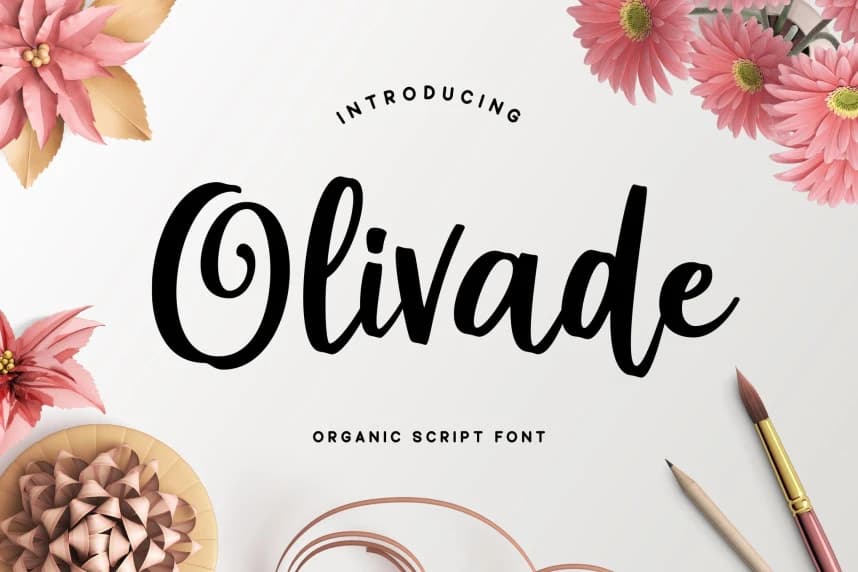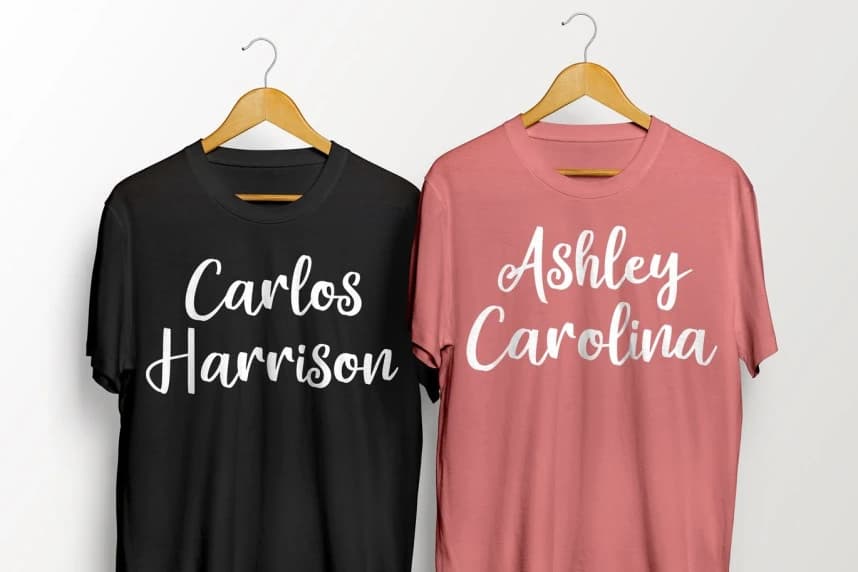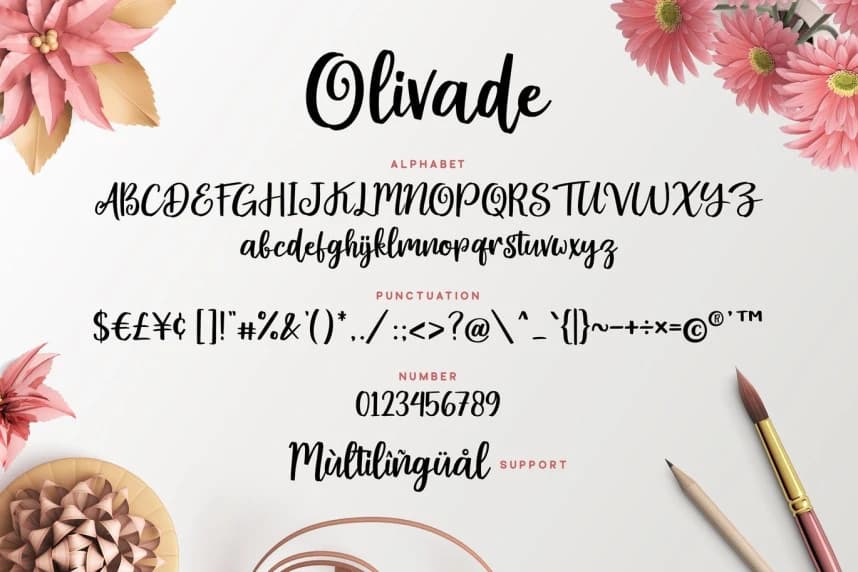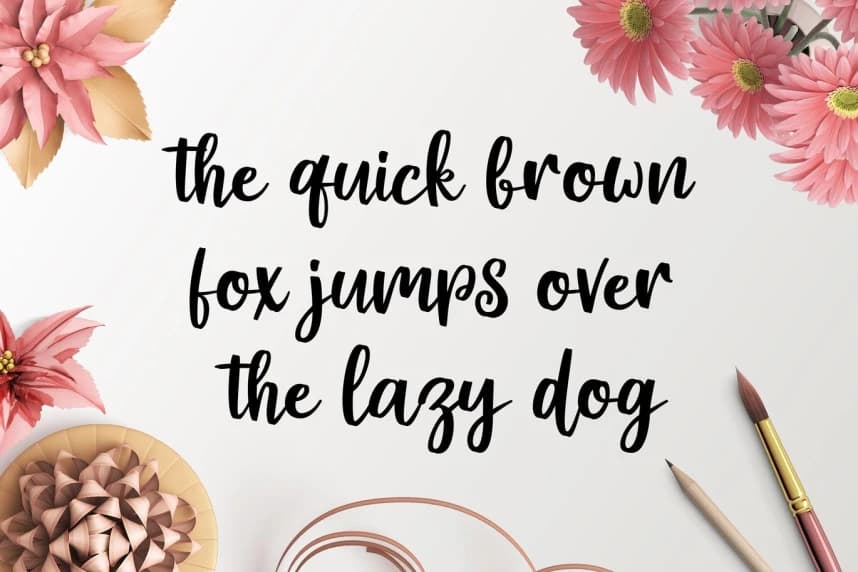
Olivade Script Font
Olivade Script Font, çok özenle tasarlanmış taze ve doğal bir el yazısı fontudur. Olivade, marka oluşturma için logo tasarımı, tipografi tasarımı, Noel kartı, ürün ambalajı, davetiye, alıntılar, tişört tasarımı, etiketler ve posterler, özel etkinlikler ve el yazısı hissi isteyen her şey için mükemme
Olivade Script Font, çok dikkatli bir şekilde tasarlanmış taze ve organik bir el yazısı fontudur. Olivade, marka oluşturma için logo tasarımında, tipografi tasarımında, Noel kartında, ürün ambalajında, davetiyelerde, alıntılar için, tişört tasarımında, etiket ve afiş tasarımında, özel etkinliklerde ve el yazısı hissine ihtiyaç duyan her şeyde mükemmel bir tercihtir.